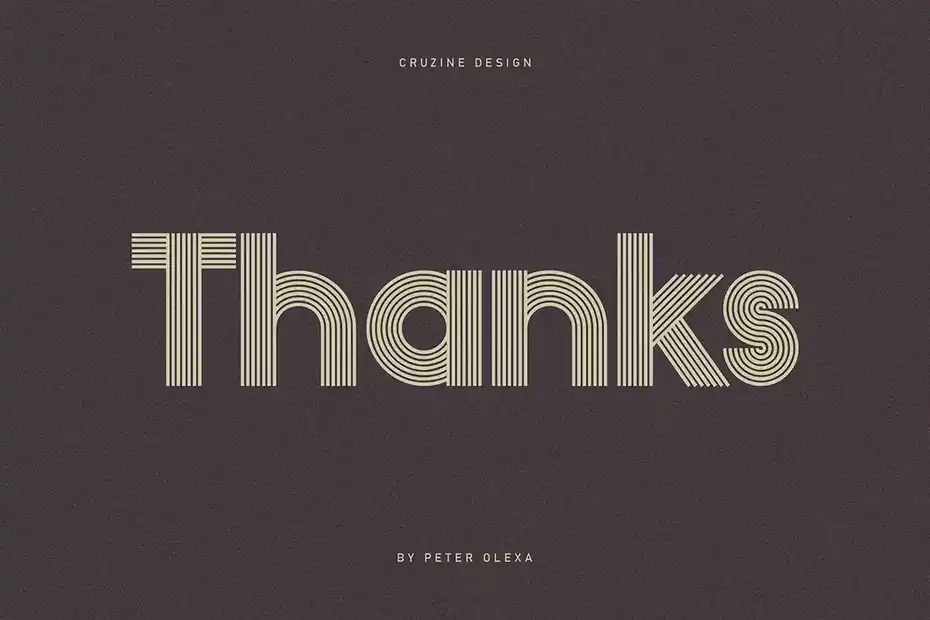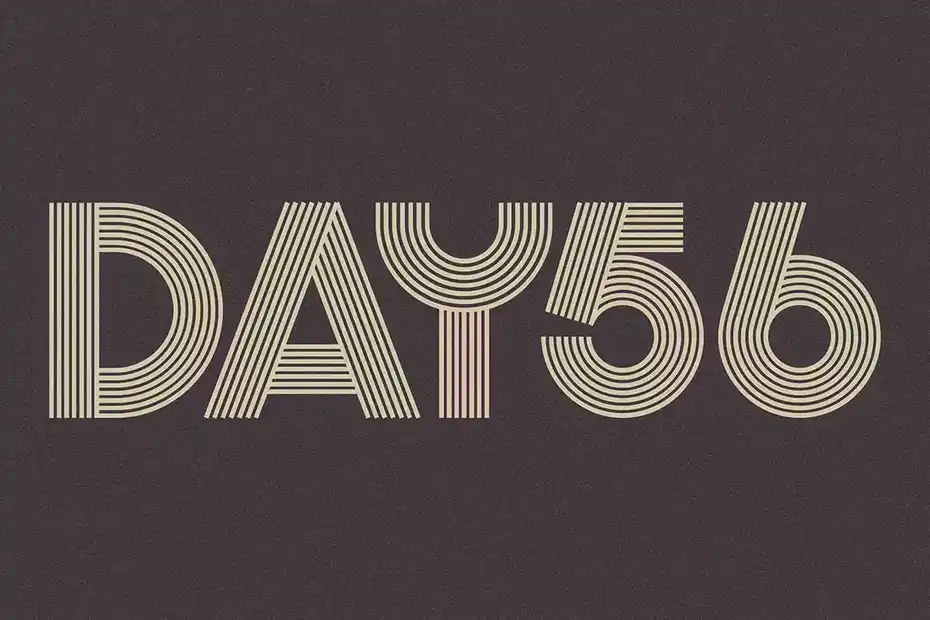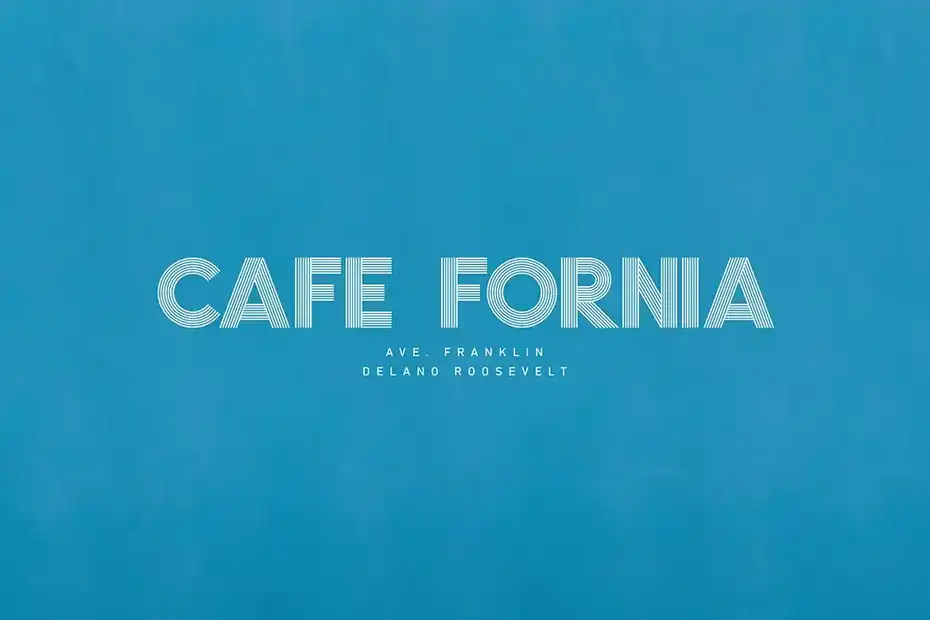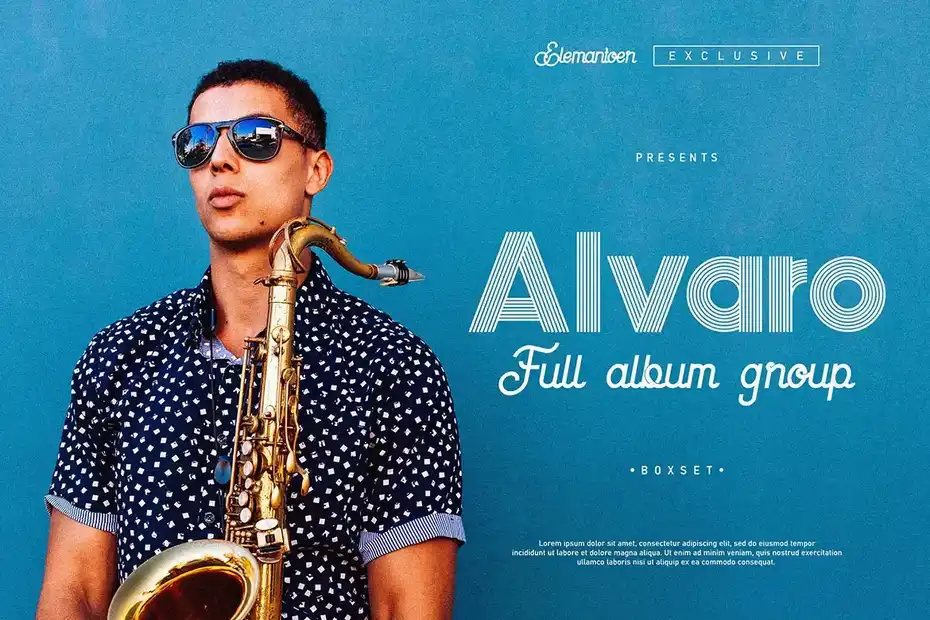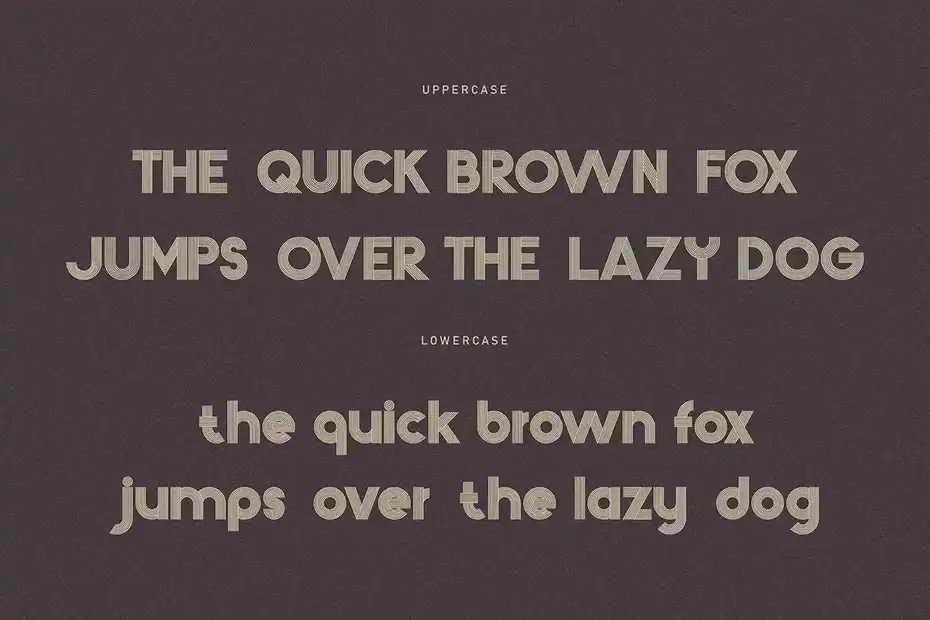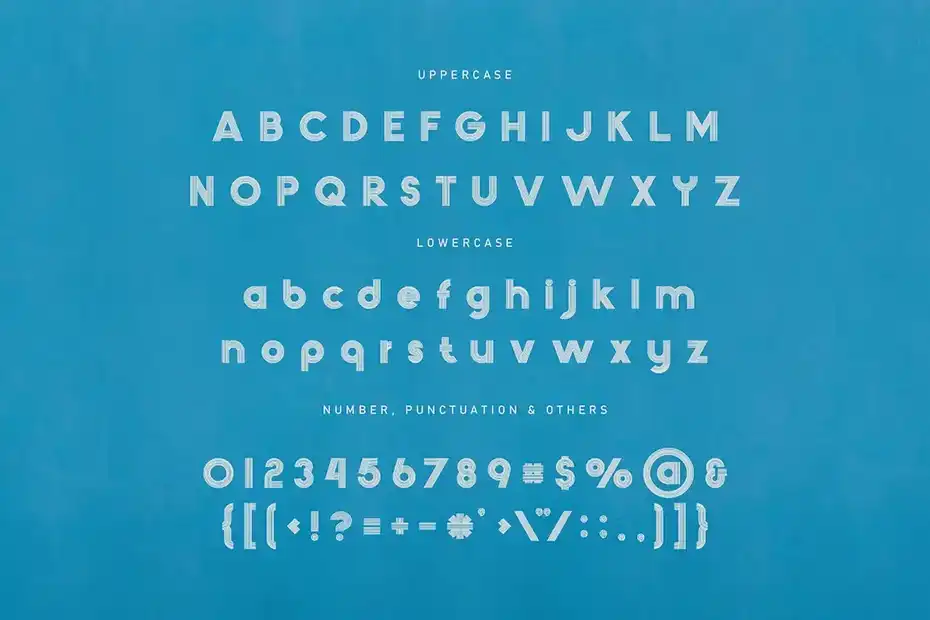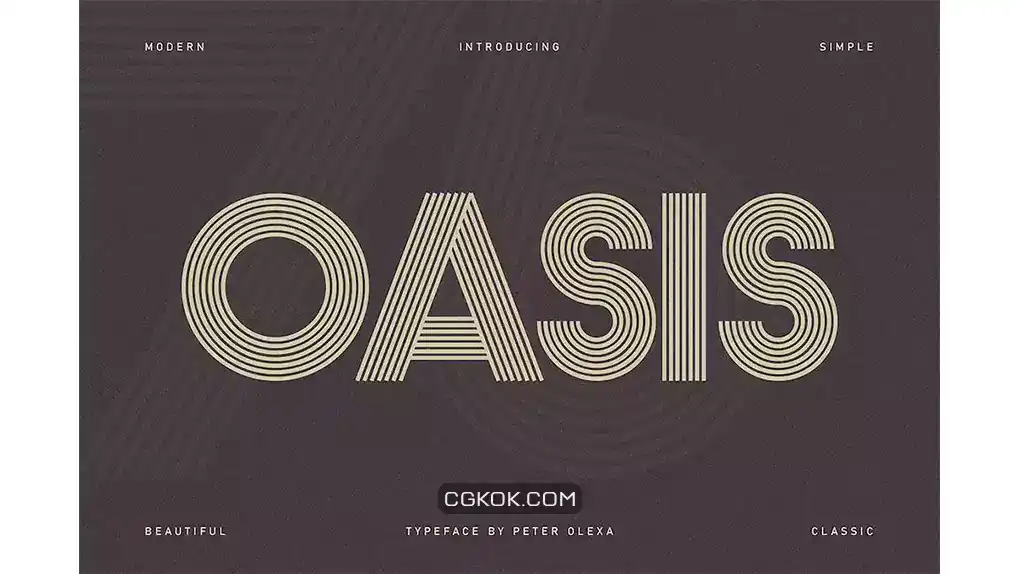
دانلود فونت انگلیسی هندسی Oasis Geometric Font
فونت انگلیسی هندسی Oasis Geometric Font : این مجموعه شامل یک فونت انگلیسی هندسی است که برای پروژه های نئون و آینده نگر مناسب میباشد.